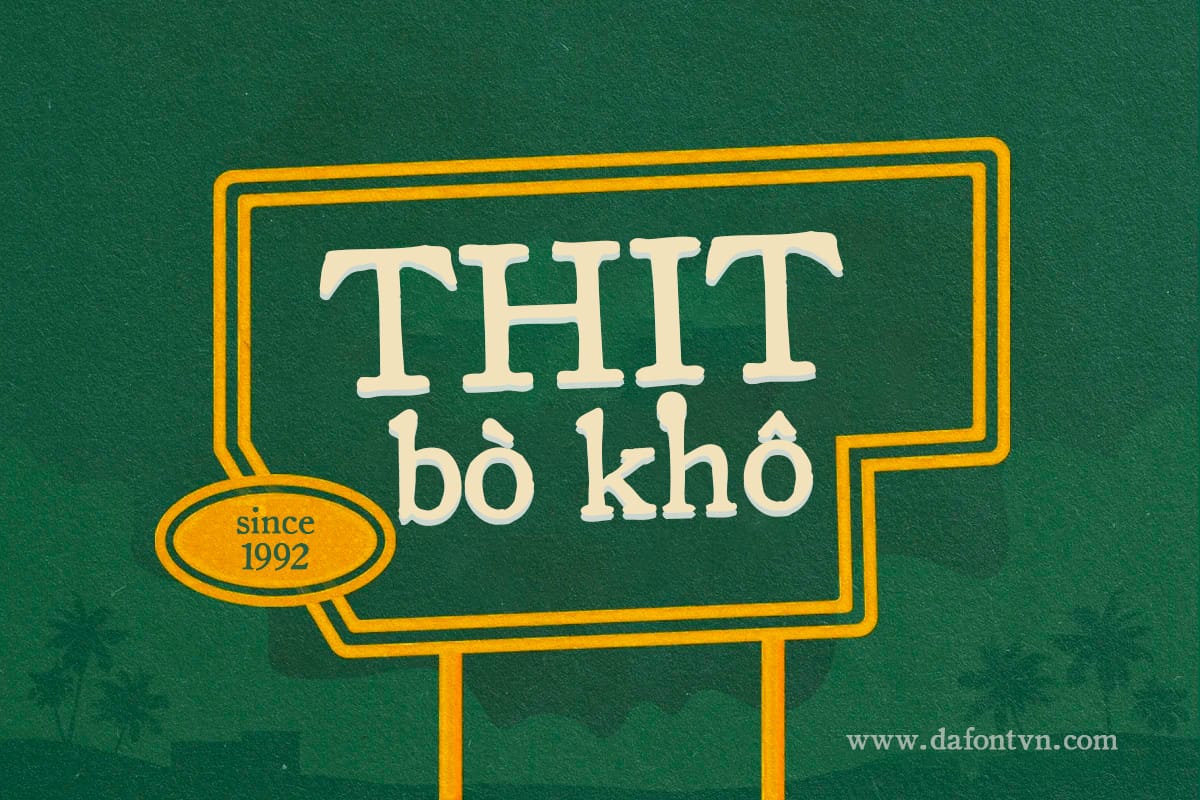
Font iCielBC OldStyle Việt hóa miễn phí nằm trong bộ font Hồi ức Sài Gòn được Việt hóa và chia sẻ miễn phí bởi iCiel. OldStyle một font chữ retro khá phù hợp cho các thiết kế kiểu xưa cũ và nhiều các thiết kế khác.